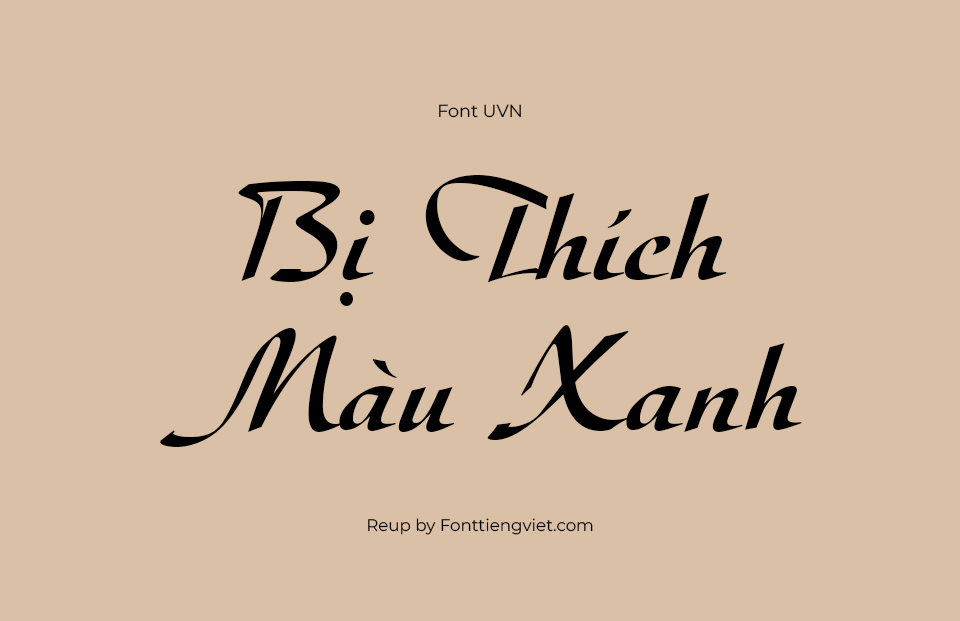
Trong thế giới thiết kế đồ họa và soạn thảo văn bản, việc lựa chọn một Font Chữ phù hợp đóng vai trò quan trọng để tạo nên sự ấn tượng. Font Việt Hóa UVN Thu Tu là một lựa chọn tuyệt vời dành cho những ai yêu thích vẻ đẹp truyền thống pha lẫn nét hiện đại. Đây là bộ font nằm trong hệ thống UVN nổi tiếng, được tối ưu hóa hoàn toàn cho bảng mã Unicode, giúp người dùng dễ dàng gõ tiếng Việt mà không lo lỗi hiển thị. Với phong cách thanh mảnh và nét chữ uyển chuyển, bộ chữ này thường xuyên được các bạn học sinh sử dụng trong các bài báo tường hoặc giáo viên dùng để trang trí giáo án điện tử thêm phần sinh động.
Đặc điểm nổi bật của Font Việt Hóa UVN Thu Tu
Bộ Font Việt Hóa UVN Thu Tu sở hữu những đường nét uốn lượn đặc trưng, mô phỏng lại lối viết chữ tay đầy nghệ thuật. Điều này giúp văn bản trở nên mềm mại và có hồn hơn so với các phông chữ hệ thống khô khan. Nhờ tính tương thích cao, bạn có thể sử dụng nó trên nhiều phần mềm khác nhau như Microsoft Word, PowerPoint hay các ứng dụng thiết kế chuyên nghiệp như Photoshop và Canva. Đặc biệt, việc cài đặt vô cùng đơn giản, chỉ cần vài thao tác giải nén và cài đặt vào thư mục Fonts của máy tính là bạn đã có thể bắt đầu sáng tạo.
Ứng dụng thực tế trong học tập và giảng dạy
Không chỉ dừng lại ở mục đích trang trí, phông chữ này còn cực kỳ hữu ích trong việc làm thiệp chúc mừng, thiết kế bìa sách hoặc làm tiêu đề cho các slide thuyết trình. Sự tinh tế của các ký tự giúp người xem cảm thấy dễ chịu và bị thu hút ngay từ cái nhìn đầu tiên. Đối với môi trường giáo dục, đây là công cụ đắc lực giúp các bài giảng trở nên gần gũi và thú vị hơn đối với học sinh.
Kết luận về bộ font chữ nghệ thuật